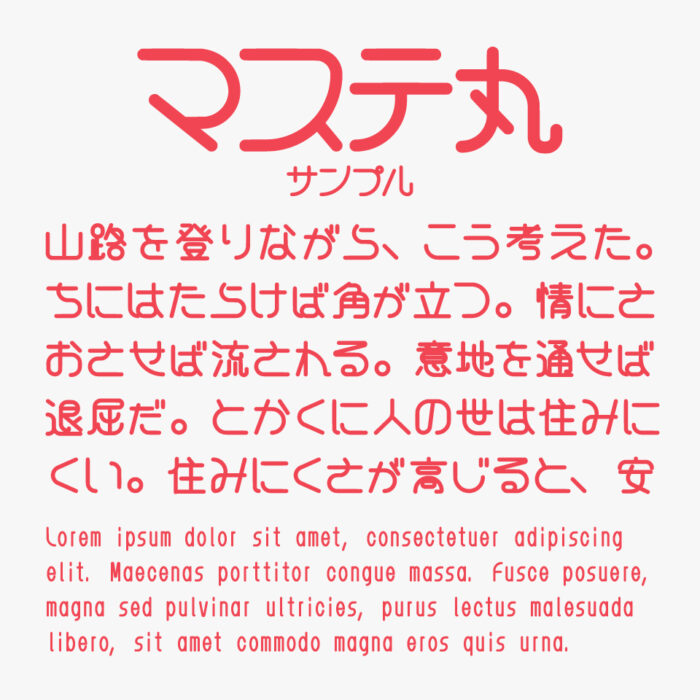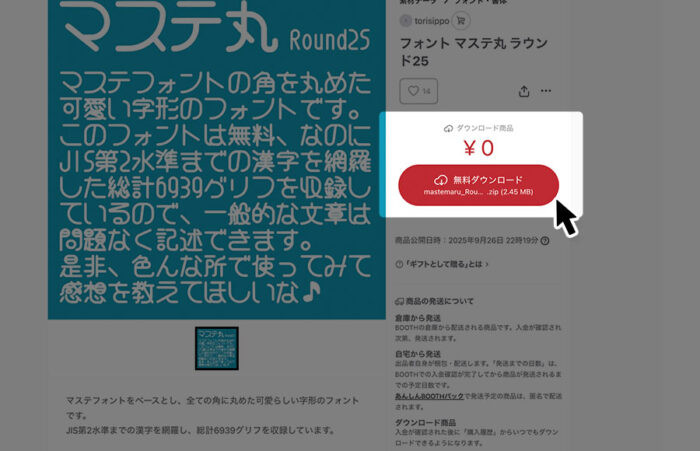
マステ丸 ラウンド25フォントは、やさしく整った角丸な線とリズム感が心地よい、可愛らしくもあり親しみやすいデザインフォントです。
角のない強めな丸みのある曲線が特徴のデザインです。全体的にスッキリとしつつも、文字のフォルムにはどこか手書きのような柔らかさが感じられ、落ち着いた雰囲気のあるフォントです。